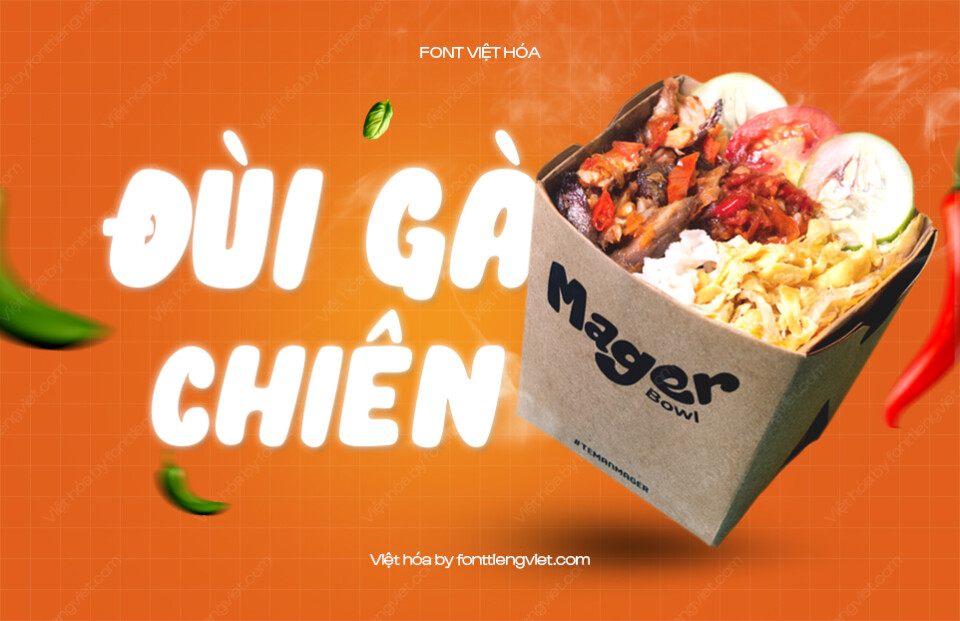
Font Việt hóa 1FTV VIP Unicorn Pop
Font Việt hóa 1FTV VIP Unicorn Pop – Lựa chọn hoàn hảo cho thiết kế trẻ trung
Giới thiệu về Font Việt hóa 1FTV VIP Unicorn Pop
Trong thế giới đồ họa hiện đại, việc tìm kiếm một bộ Font Miễn Phí có phong cách đáng yêu và chuyên nghiệp luôn là ưu tiên hàng đầu của các nhà thiết kế. Font Việt hóa 1FTV VIP Unicorn Pop nổi lên như một giải pháp lý tưởng dành cho những ai yêu thích sự ngọt ngào, bay bổng nhưng vẫn đảm bảo tính ứng dụng cao. Đây là bộ phông chữ được tinh chỉnh kỹ lưỡng về dấu tiếng Việt, giúp người dùng dễ dàng sử dụng trong các phần mềm thiết kế phổ biến mà không lo lỗi hiển thị hay mất nét.
Đặc điểm nổi bật của phông chữ Unicorn Pop
Phong cách thiết kế kẹo ngọt
Đúng như tên gọi, Font Việt hóa 1FTV VIP Unicorn Pop mang trong mình hơi thở của sự mơ mộng và vui tươi. Với những đường nét tròn trịa, mềm mại và cấu trúc phá cách, bộ font này gợi liên tưởng đến thế giới thần tiên của những chú kỳ lân. Các nét chữ được bo góc tinh tế, tạo cảm giác thân thiện và gần gũi đối với người xem, đặc biệt là lứa tuổi học sinh và trẻ em. Điều này giúp tác phẩm trở nên sinh động và có sức hút tự nhiên hơn.
Khả năng ứng dụng đa dạng
Không chỉ dừng lại ở vẻ ngoài bắt mắt, bộ font này còn có tính linh hoạt rất lớn. Bạn có thể sử dụng nó cho các bài thuyết trình học đường, thiết kế bìa sách, thiệp chúc mừng hoặc các ấn phẩm quảng cáo cho ngành hàng đồ chơi và giáo dục. Sự kết hợp giữa yếu tố thẩm mỹ và kỹ thuật việt hóa chuẩn xác giúp phông chữ này luôn nằm trong danh sách ưu tiên của cộng đồng sáng tạo tại Việt Nam.